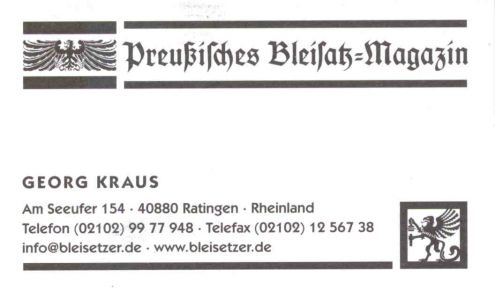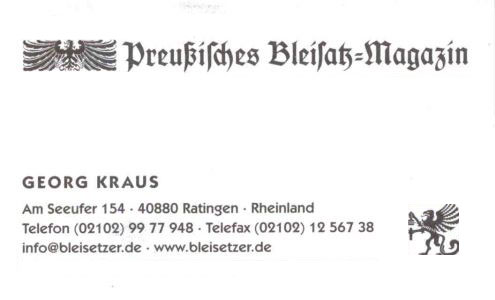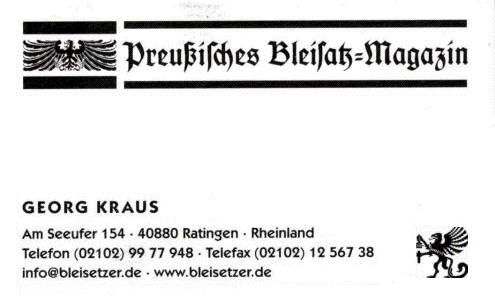
Preußische Visitenkarten
Es galt, die neuen Visitenkarten und Briefbogen des Preußischen Bleisatz-Magazin neu zu gestalten.
Hierbei wurden neue Logos adaptiert, die sowohl auf der Webseite, als auch auch allen Drucksachen des PBM verwendet werden sollten.
Verwendete Schriften:
Koch-Fraktur
Erstguß 1908
Kabel bold, Kabel demibold
Erstguß 1929 bzw. 1930
Alle Schriften von Rudolf Koch
Schriftgießerei Gebr.Klingspor, Offenbach am Main
Das Design soll den Charakter des PBM wiedergeben bzw. ein Corporate Identity schaffen:
Die Assoziation mit Preußen soll polarisieren
Der Gesamtcharakter soll konservativ wirken, Vertrauen und Zuverlässigkeit vermitteln. Die Entscheidung, als Grundschrift für den VK-Text die Kabel zu wählen, ergab sich aus der pragmatischen Sicht, daß ein vollständiger Fraktur-Text mangels besserem Wissen zu Irrtümern beim Kunden hätte führen können. Somit sollte es eine Grotesk-Schrift sein, die die recht moderne Anmutung des Greifs und der Preußischen Flagge unterstützt.
Die Realisierung hat ein junger Kollege vorgenommen, mit dem ich so gut wie jede typographische Entscheidung habe diskutieren müssen. Nicht immer habe ich mich durchsetzen können - letztendlich, so sehe ich das jetzt, zu meinem eigenen Besten.
Saubere Sache! Irgend etwas stimmt für mich allerdings noch nicht ganz: Ist es das Nebeneinander der fetten Balken beim Adler und der schmalen beim Namenszug? Ich weiß es (noch) nicht ganz …
die balken hätte ich auch lieber fetter gemacht und der flagge angepasst,
aber es soll leute geben die sich aufregen, wenn das fax beim ausdruck
zuviel toner verschluckt. :roll: mir gefällts ansonsten, auch wenn ich
den kopf und den fuß auf den vk lieber 5 mm weiter nach innen
gerrückt hätte ...
was sagst du zur qualität des druckes?
läuft der adler im buchdruck zu?
zwei Dinge,
1. Die Karte wirkt etwas "überladen" zu sehr Z-artige Blickführung.
2. Die Strichstärke der beiden Tierchen harmoniert nicht mit den dicken Linien.
Der Preußenadler ist nun tatsächlich ein Preußenadler mit Reichsapfel und Zepter?
Wie sähe die Karte aus ohne dicke Linie und das zweite Signet unten?
Die Schriftmischung ist stimmig und paßt auch thematisch gut. - Die Karte wird auch trotz meiner Anmerkungen gut funktionieren. Also nicht die Auflage einstampfen. :-)
zu 1.
das überladene ließ sich schlecht vermeiden, auf die idee mit der
z-artigen-blickführung bin ich noch garnicht gekommen — aber,
nach längerem betrachten, finde ich das gar nicht so übel.
zu 2.
stimmt, ich hatte georg oft vorgeschlagen die tierchen zu stilisieren
damit sie besser zu den dicken linien passen, außerdem hatte ich
angst das die flügelt und die anderen details im druck zuschmieren.
aber eigentlich ist das orginal ja so gewesen, der preußenadler ist
ja extra dafür als klischee gemacht wurden um in eine fahne ein-
gesetzt zu werden.
nein, der adler hat kein zepter und keinen apfel.
er hat das gleich buchdrucker und setzer werkzeug in den fängen wie
der greif. anders als das original, es passt nun besser zum greif.
ich poste morgen mal die beiden originale.
generell:
die ausstattung sollte nicht edel wirken, sondern typisch preußisch – fett.
bei der schriftmischung haben wir lange mit den verschiedenen schnitten
herumprobiert. die kabel war meine erste idee.
bold/medium in der adresse und book im schriftverkehr haben sich dann
durchgesetzt. die original linotype kabel war auch kurz im gespräch, wirkte
aber dann eindeutig zu filigran für einen großen preußen. ;)
Die Linien (alle) finde ich überflüssig – ganz abgesehen davon, daß die Strichstärken ohne Not unterschiedlich sind. Aber der Bleisetzer freut sich meist zu gerne über jedes druckende Element anstelle des ganzen Blindmaterials was er verbraten muß. Ich kenne das. (Zwischenprüfung zum Schriftsetzer habe ich noch in Blei gemacht. 22 Zeilen!)
das obere Beispiel des Kollegen sieht viel offener aus - im Sinne von "gefälliger".
Es beinhaltet nur zwei grundsätzliche Probleme, die durch eine solche Umsetzung entstehen:
a) In allen Print-Vorlagen sollte links oben eine Preußische Flagge eingebaut werden. Im oberen Beispiel gibt es aber keine mehr. Das wäre nicht akzeptabel gewesen.
b) Es gibt ein drucktechnisches Problem, das durch die Linien gelöst wird: